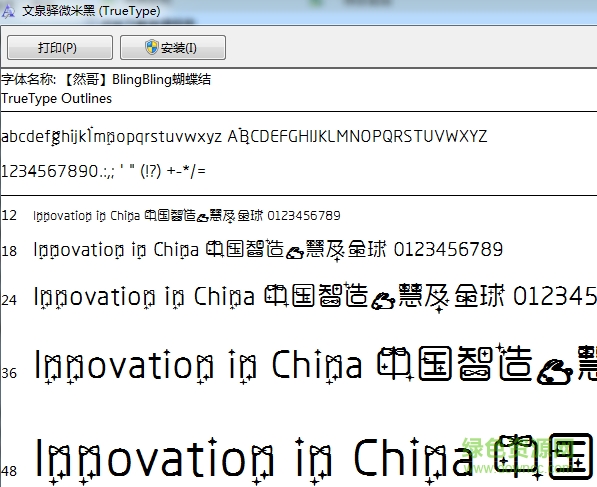
戀愛蝴蝶結體
戀愛蝴蝶結字體是一款超好用的中文個性字體,字體中穿插的可愛蝴蝶結極大的滿足的女人的少女心,對于平面設計來說,非常適用于女士的廣告設計,需要的用戶就趕快來綠色資源網(wǎng)免費下載收藏吧!
戀愛蝴蝶結字體是一款極具個性的字體,該字體十分飄逸,彰顯了自己的個性,有喜歡的朋友可以來綠色資源網(wǎng)下載使用!